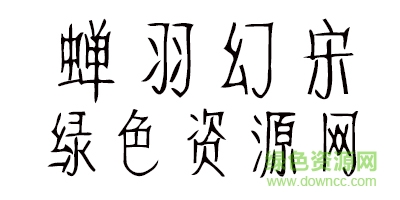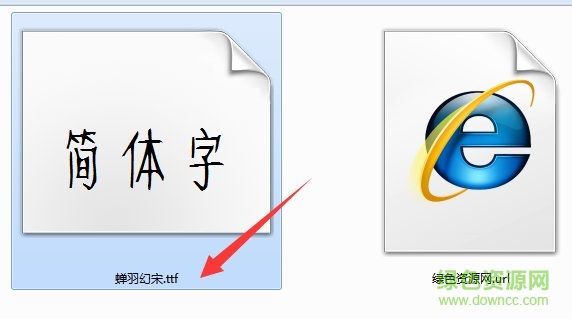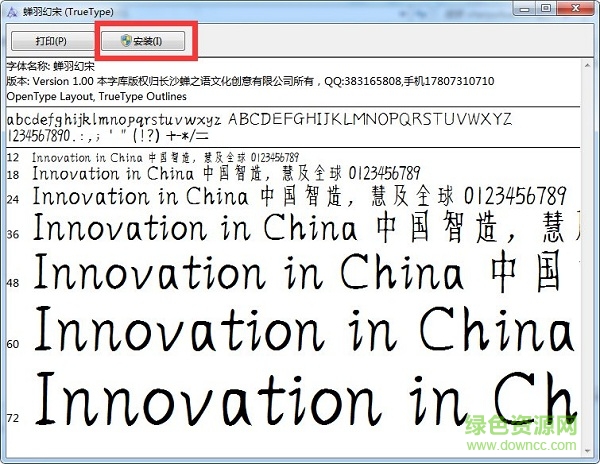
蟬羽幻宋字體ttf在多個(gè)行業(yè)被廣泛使用。這個(gè)字體無(wú)論是用來(lái)書(shū)寫(xiě)中文還是英文都是個(gè)不錯(cuò)的選擇!常被用來(lái)設(shè)計(jì)廣告、海報(bào)等使用!需要的用戶(hù)快來(lái)下載吧。
蟬羽幻宋字體ttf是一個(gè)非常漂亮的藝術(shù)字體,是適合手寫(xiě)藝術(shù)設(shè)計(jì)的字體,該字體支持android、Windows、Mac等系統(tǒng)。喜歡的用戶(hù)歡迎在綠色資源網(wǎng)下載安裝使用。